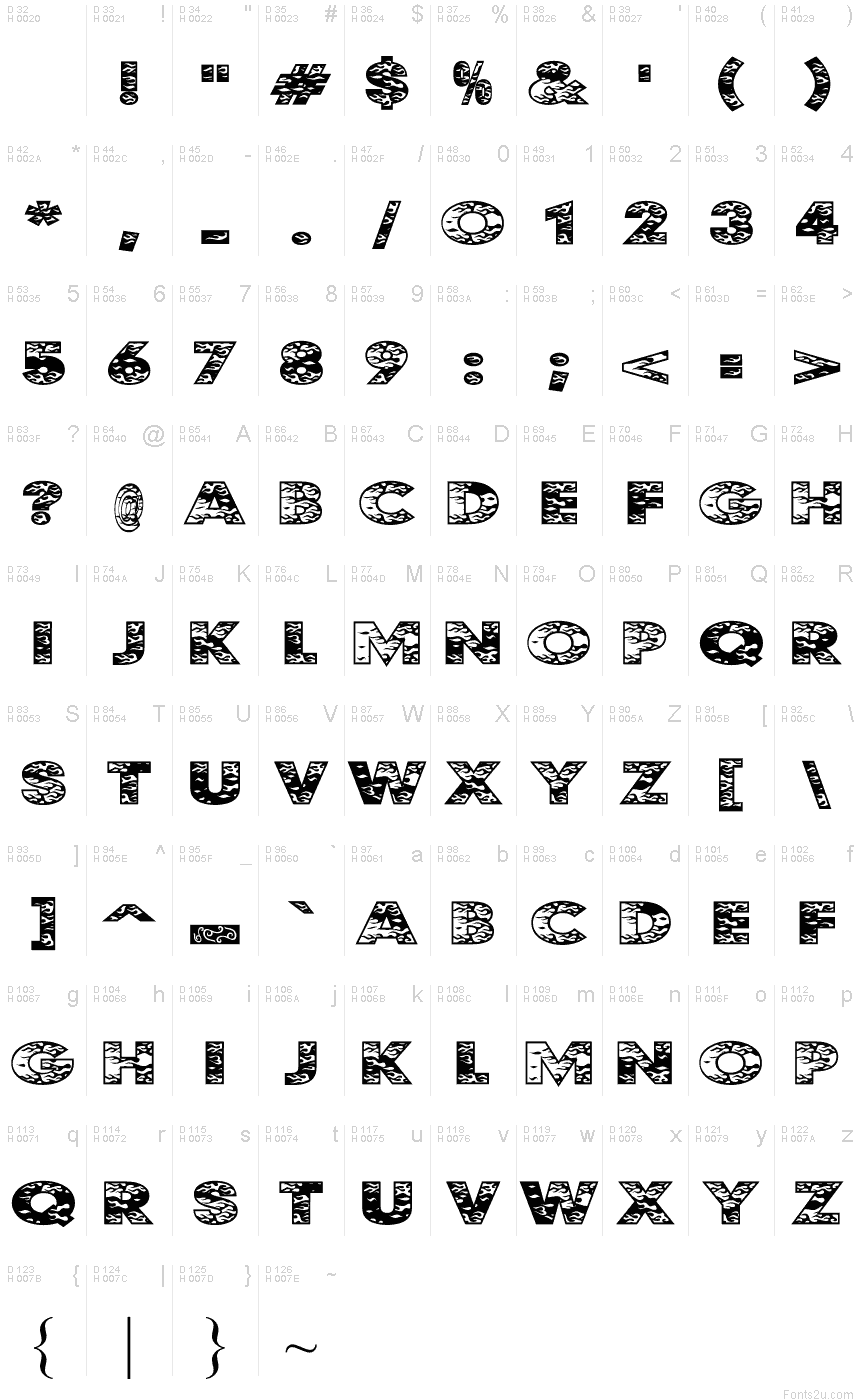
UKIJ Esliye Neqish od Uyghur Computer Science Association to darmowy krój displayowy o wyrazistym, rzeźbionym wyglądzie, stworzony z gęstych, falistych wycięć. Litery są masywne i plakatyczne, a szerokie blokowe kształty przełamują powtarzające się pofalowania, dzięki czemu font przypomina bardziej słoje drewna, wodę lub kamuflaż niż zwykłą, szorstką teksturę.
Doskonale sprawdza się na ulotkach muzycznych, grafikach streetwearowych, plakatach imprezowych, w tytułach gier i na opakowaniach, wszędzie tam, gdzie darmowy font musi wyróżniać się silną sylwetką i żywą powierzchnią. Wykorzystaj go w krótkich nagłówkach, hasłach na okładki lub inicjałach typu monogram, gdy chcesz, aby ciężkie formy budowały układ, a wzorzyste wnętrza dodawały słowom dynamiki.